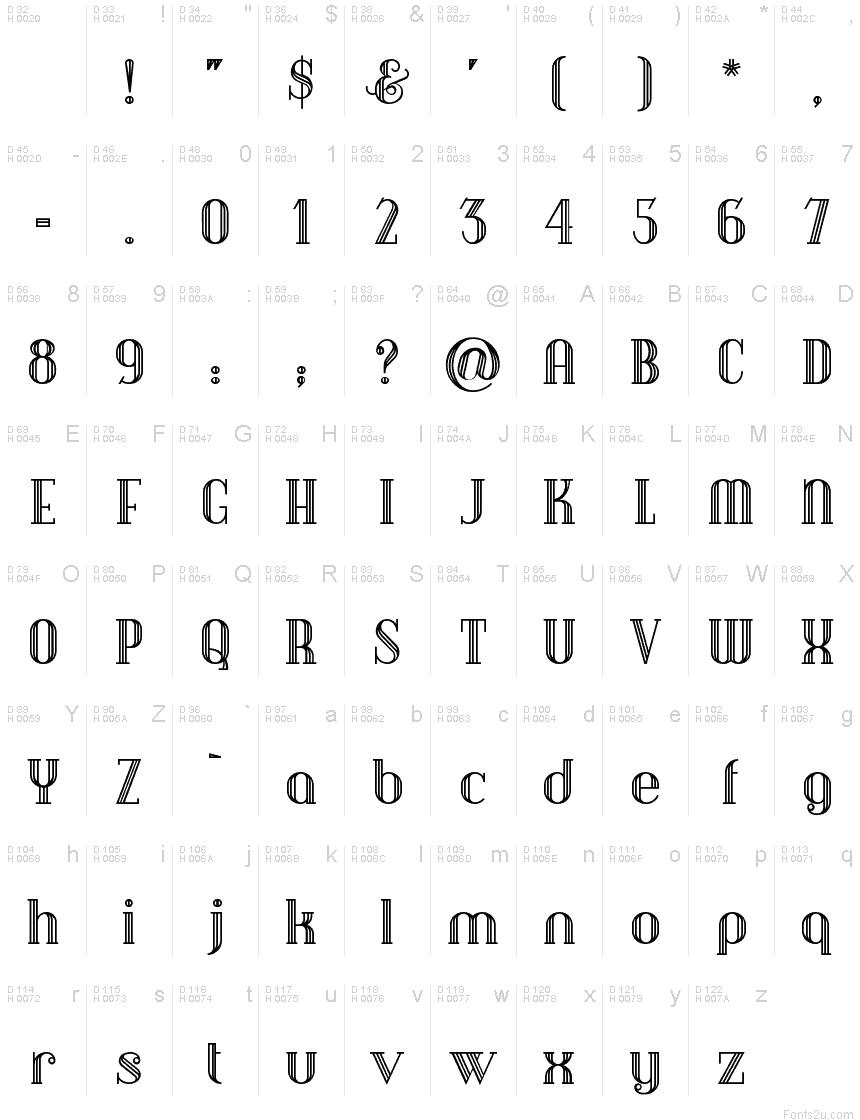
Krój pisma DebonairInline autorstwa Nicka Curtisa to darmowy, retro font typu display, który zamienia każde słowo w neonowy spektakl. Wysokie, eleganckie litery są ozdobione wyraźnymi liniami, co nadaje im wygląd polerowanych chromowanych kolumn ze starego szyldu. Rytm tych pionowych linii sprawia, że nawet pełne fantazji krzywizny zachowują wyważony i dopracowany charakter, dodając stylu glamour bez zbędnego skomplikowania czy utraty czytelności.
Dzięki DebonairInline nagłówki wyglądają, jakby pochodziły z plakatu z epoki jazzu lub karty koktajli w stylu vintage. Ten darmowy font świetnie sprawdza się na plakatach eventowych, w brandingu barów i lokali typu speakeasy, na okładkach książek, opakowaniach, zaproszeniach oraz w każdej komunikacji wizualnej, gdzie chcesz połączyć dramaturgię z umiarem. Warto łączyć go z prostym, geometrycznym bezszeryfowym krojem przy mniejszych rozmiarach, aby DebonairInline mógł w pełni zabłysnąć w dużych tytułach i logotypach.